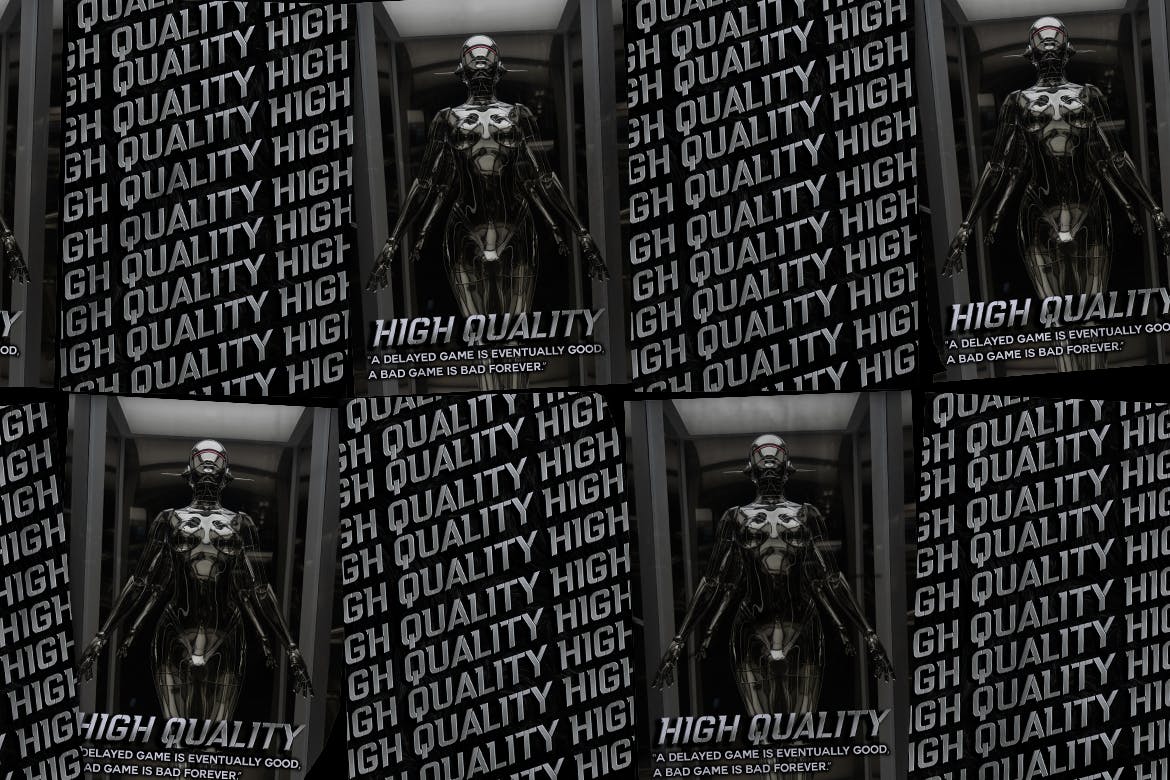
Lokvore A Modern Typeface
فونت Lokvore با طراحی آینده‌نگر، مناسب برای پروژه‌های گرافیکی شما.
فونت Lokvore طراحی تایپوگرافی شما را مدرن‌تر و آینده‌نگرانه‌تر می‌کند. چه به دنبال فونتی برای طراحی پروژه‌های بازی، بروشورهای موسیقی، پوسترهای فیلم یا دیگر گرافیک‌ها باشید، این لیست گزینه‌های زیادی را در اختیار شما قرار می‌دهد. این فونت با کدگذاری PUA ارائه شده است که به شما امکان دسترسی آسان به تمام نمادها و لیگاتورهای شگفت‌انگیز را می‌دهد!
ویژگی‌ها:
• حروف بزرگ و کوچک
• نسخه‌های جایگزین
• لیگاتورها
• اعداد
• نقاط
• پشتیبانی از چند زبان